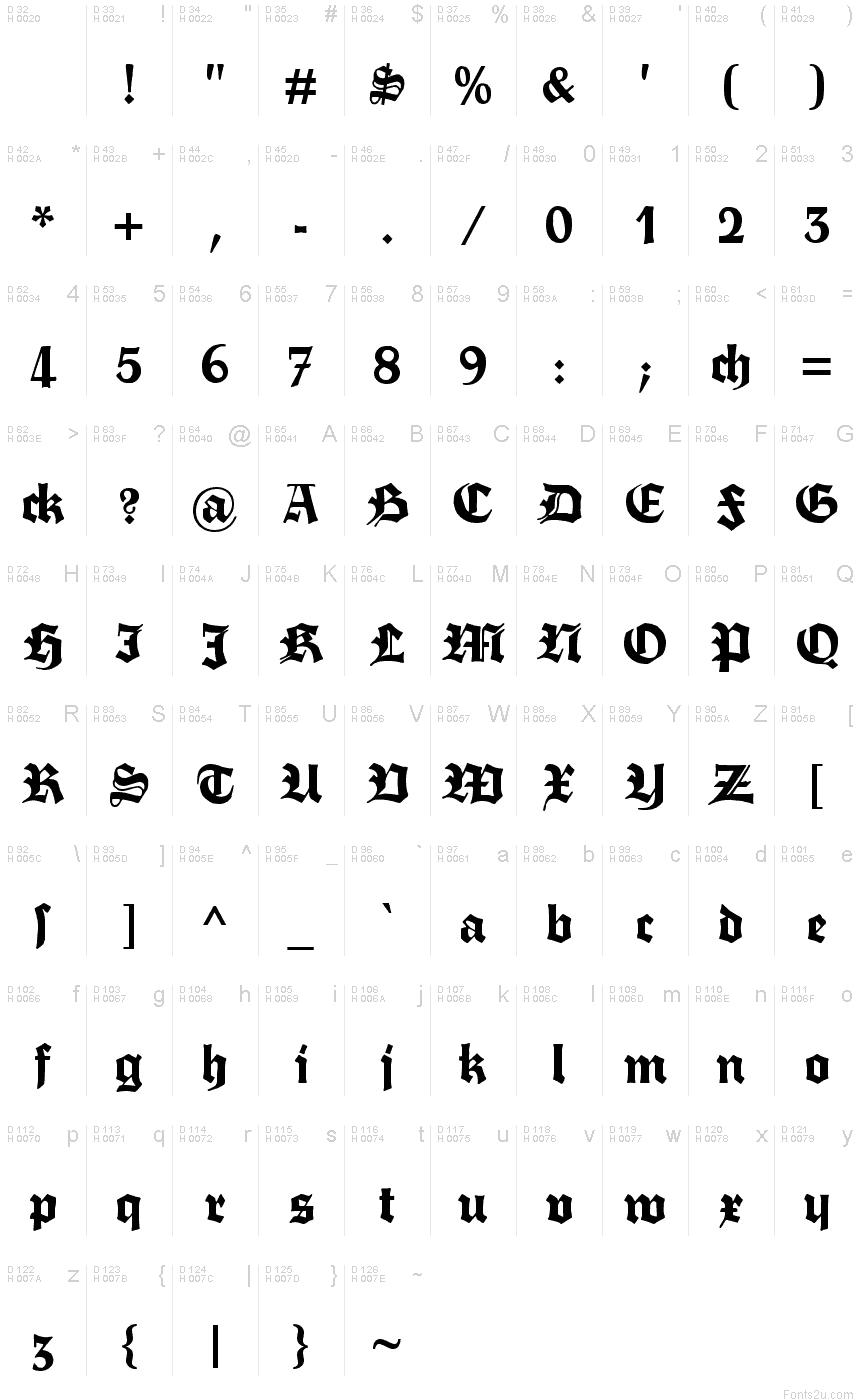
Fette Trump-Deutsch von Dieter Steffmann ist eine kostenlose gotische Schriftart. Ihre schweren, tintenartigen Striche und scharf gebrochenen Kurven erinnern an klassische Blackletter-Stile, jedoch mit einer leicht übersteigerten Kühnheit, die an einen geschnitzten Holzschnitt erinnert. Die Buchstaben fügen sich zu einem dichten, strukturierten Zeilenbild zusammen, das zeremoniell und leicht düster wirkt – perfekt, um einem Layout sofort eine dunkle, historische Note zu verleihen.
Mit Fette Trump-Deutsch erhalten Überschriften und Logos die Wucht von Bannern oder Steininschriften. Sie glänzt daher besonders bei Branding für Metal-Bands, Fantasy-Buchcovern, Etiketten für Bier oder Met, Tattoo-Flash, Spieletiteln und Postern für Mittelalter-Events. Setzen Sie diese kostenlose Schrift groß ein, um die Atmosphäre wirken zu lassen, und kombinieren Sie sie mit einer schlichten, modernen serifenlosen Schrift für den Fließtext, um die Lesbarkeit zu gewährleisten.
Fette Trump-Deutsch geschaffen von Prof. Georg Trump, 1936. Digitalisiert durch Dieter Steffmann, Kreuztal.